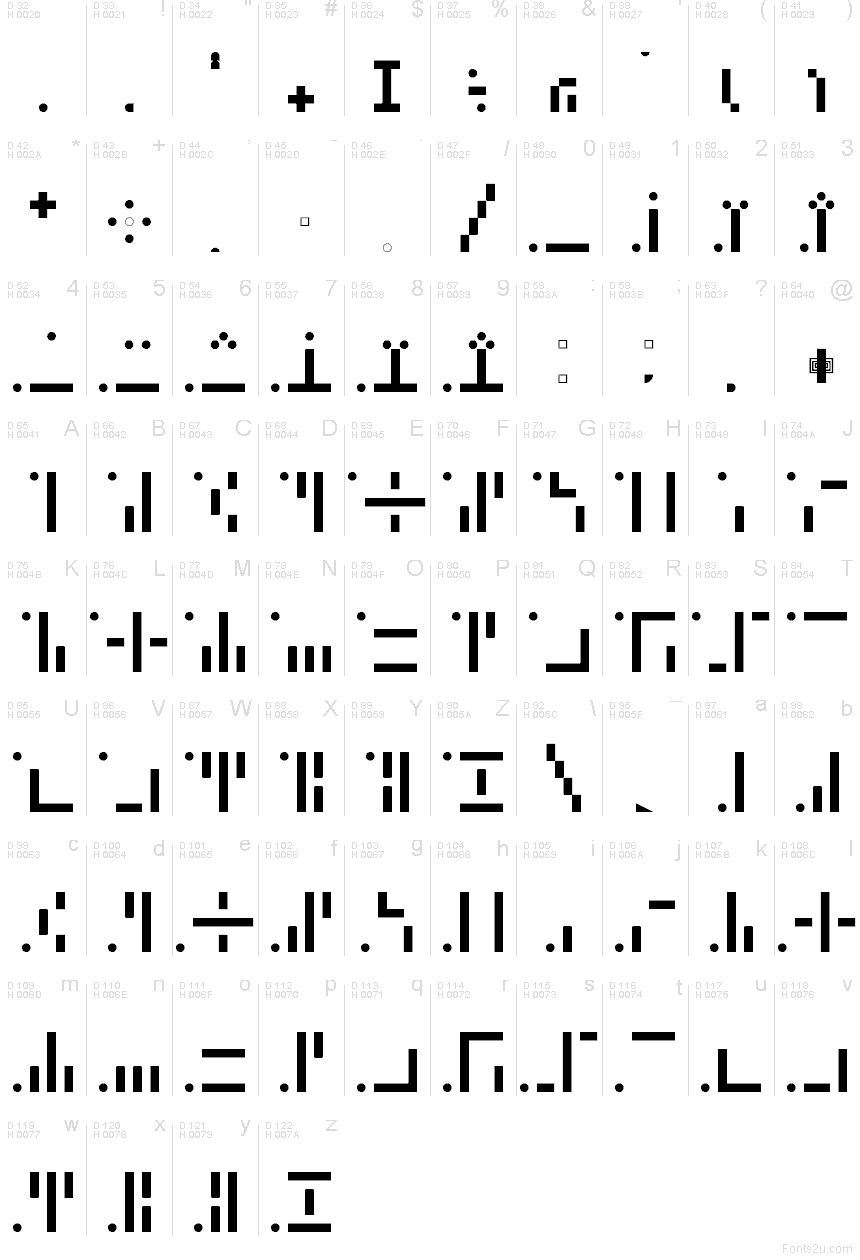
Helios Regular
La police Helios de Ccbmonster est une police dingbats gratuite composée de formes géométriques simples : cercles, petits traits et blocs verticaux ou horizontaux agencés de manière sobre et modulaire. L'ensemble s'apparente davantage à un système de signes qu'à une décoration, avec des formes répétées de points et de lignes qui assurent la cohérence de la famille.
Helios est une police gratuite idéale pour les logos, les icônes d'applications, les étiquettes, les accents infographiques, les séparateurs et les ornements d'affiches nécessitant un jeu de symboles compact. Ses formes épurées s'adaptent parfaitement aux mises en page qui demandent des marqueurs répétés ou des séparateurs graphiques sans surcharger le design.